Font VNI là gì?
Font VNI là hệ thống mã hóa và phông chữ tiếng Việt được phát triển cho hệ điều hành Windows. Tên gọi VNI là viết tắt của Việt Nam Input, dùng để giúp máy tính nhận diện và hiển thị chính xác chữ cái, dấu tiếng Việt trong quá trình soạn thảo văn bản. Khi máy tính chưa cài font VNI, các file sử dụng bảng mã này thường bị lỗi ký tự hoặc sai dấu.
Bộ font VNI bao gồm nhiều kiểu chữ khác nhau, đáp ứng nhu cầu gõ tiếng Việt trong văn bản, thiết kế và trình chiếu. Nhờ hỗ trợ đầy đủ tiếng Việt có dấu, font VNI giúp người dùng làm việc ổn định với các tài liệu cũ và tránh tình trạng lỗi font khi mở file trên Word, Excel hoặc một số phần mềm đồ họa.
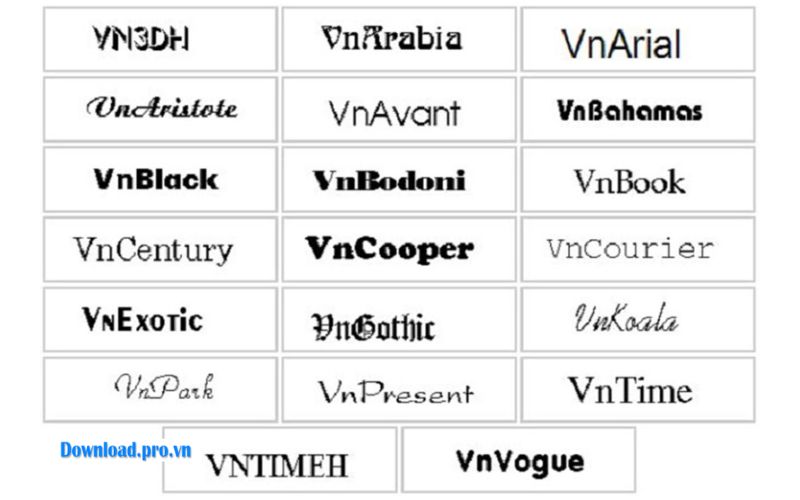
- Font VNI là hệ thống font chữ tiếng Việt
Các loại font VNI phổ biến
Bộ font VNI không giới hạn ở một kiểu chữ duy nhất mà bao gồm nhiều font khác nhau, mỗi font phù hợp với một mục đích sử dụng riêng.
- VNI-Times: Font chữ có chân, thường dùng cho soạn thảo văn bản trên Word, Excel và PowerPoint. Nhiều tài liệu cũ mặc định sử dụng font này nên cần cài đặt để tránh lỗi hiển thị.
- VNI-Arial: Font không chân, hình thức hiện đại, dễ đọc trên màn hình. Thường xuất hiện trong slide trình chiếu và một số file thiết kế cơ bản.
- VNI-Courier: Font chữ có độ rộng ký tự cố định. Phù hợp cho lập trình, bảng biểu và các tài liệu kỹ thuật cần căn chỉnh ký tự chính xác.
- VNI-Tahoma: Kiểu chữ tương tự Arial nhưng gọn hơn. Thường dùng trong biểu mẫu hoặc tài liệu cần hiển thị nhiều nội dung trên một trang.
- VNI-Helvetica: Font sans serif với nét chữ đều, rõ ràng. Phù hợp cho tiêu đề hoặc nội dung ngắn trong tài liệu trình chiếu.
- VNI-Avo: Font trình bày, hay dùng cho tiêu đề, banner hoặc tài liệu thiết kế cũ cần tạo điểm nhấn.
- Có rất nhiều loại font VNI
Kết luận